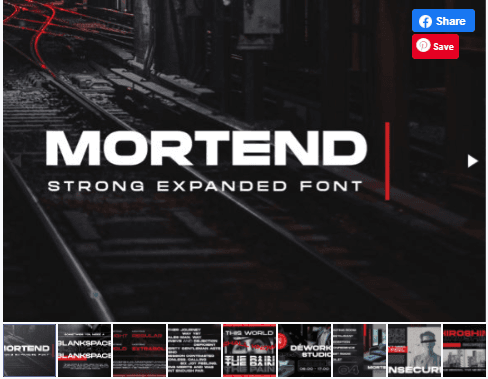
Mortend Font
Mortend - это смелый и футуристический шрифт без засечек. Мастерски разработанный, чтобы стать настоящим фаворитом, этот шрифт может воплотить каждую вашу творческую идею на высшем уровне!